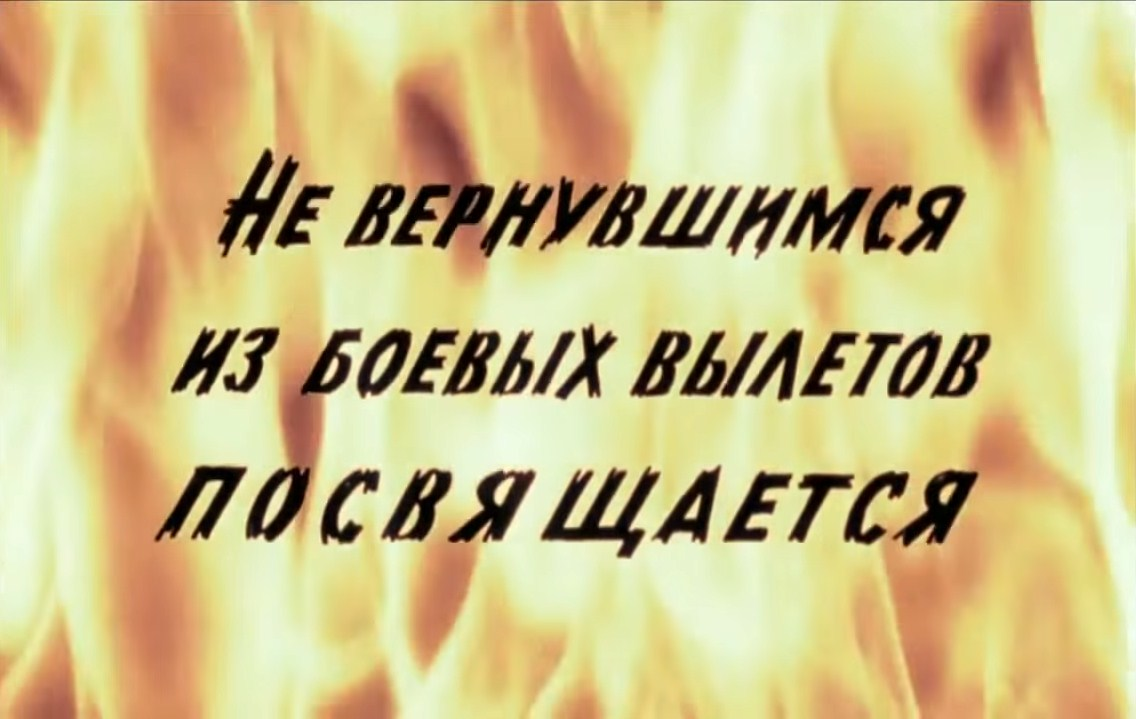
Ищу шрифт⁠⁠
Очень нужен шрифт который использовался в титрах к фильму "В бой идут одни старики".
Уже тысячи шрифтов пересмотрел но подходящий так и не нашел.
Очевидно, что заставка была нарисована вручную, а не шрифтом. Тогда все афиши и заставки рисовались вручную. А типографских шрифтов было раз-два и обчёлся. И все они были для типографий, а не кино.